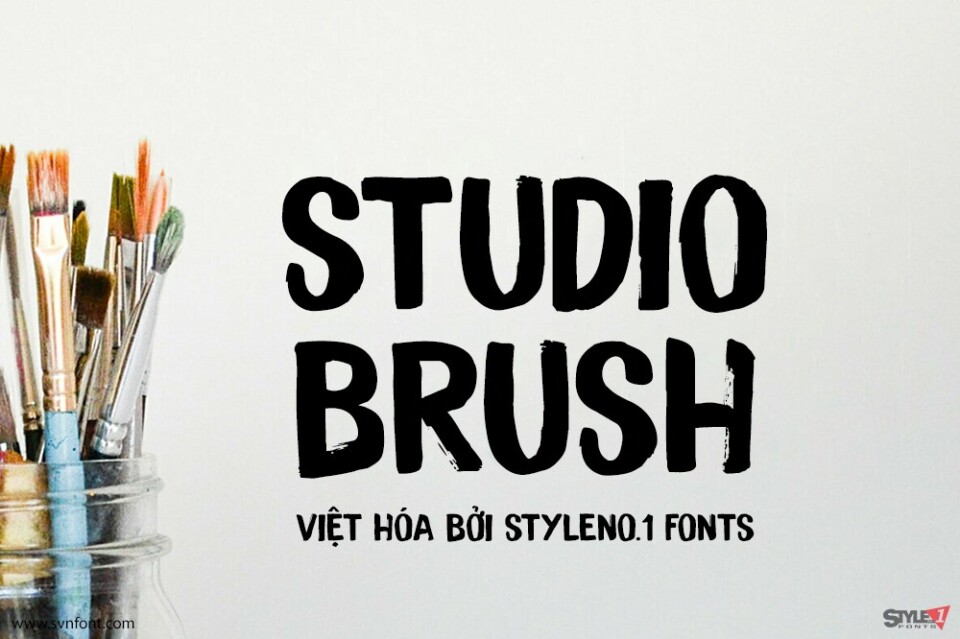
Font việt hóa SVN Studio Brush
Khám phá sức sáng tạo đột phá cùng bộ Font việt hóa SVN Studio Brush
Giới thiệu về Font việt hóa SVN Studio Brush trong thiết kế
Trong thế giới đồ họa hiện đại, việc lựa chọn một Font Miễn Phí có phong cách thủ công luôn là ưu tiên hàng đầu của các nhà thiết kế trẻ. Font việt hóa SVN Studio Brush chính là một tác phẩm nghệ thuật tiêu biểu, mang đến vẻ đẹp phóng khoáng và mạnh mẽ của những nét cọ vẽ tay. Được tối ưu hóa hoàn toàn cho bảng mã Telex, bộ phông chữ này giúp người dùng dễ dàng thể hiện những thông điệp tiếng Việt đầy cảm xúc mà không lo lỗi hiển thị. Đây là lựa chọn hoàn hảo cho các dự án yêu cầu tính cá nhân hóa cao.
Đặc điểm nổi bật của phông chữ
Bộ Font việt hóa SVN Studio Brush sở hữu những đường nét thô mộc, mô phỏng chân thực từng sợi lông cọ và vết mực loang tự nhiên. Sự không hoàn hảo có chủ đích của nó tạo nên một sức hút kỳ lạ, giúp các tiêu đề poster hay bìa sách trở nên sống động hơn bao giờ hết. Đặc biệt, bộ font này rất phù hợp với môi trường giáo dục, giúp học sinh thực hiện các dự án thuyết trình hoặc làm báo tường thêm phần ấn tượng và độc đáo.
Cách ứng dụng Font việt hóa SVN Studio Brush hiệu quả
Để tận dụng tối đa vẻ đẹp của font chữ này, bạn nên sử dụng chúng cho các cụm từ ngắn hoặc tiêu đề lớn thay vì các đoạn văn dài. Sự tương phản giữa nét đậm và nhạt giúp tạo điểm nhấn thị giác cực mạnh. Ngoài ra, việc kết hợp với các tông màu rực rỡ sẽ làm tăng tính thẩm mỹ cho tác phẩm đồ họa của bạn.
Lời kết cho cộng đồng thiết kế